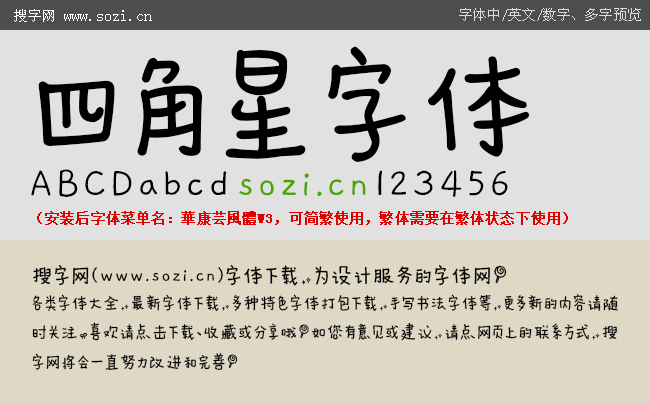
四角星字體
搜字網(wǎng)給大家提供一款卡通手寫風(fēng)格的手機(jī)中文字體下載。名字叫四角星字體,這款手機(jī)字體是以仿照兒童手寫風(fēng)格的卡通手寫字體華康蕓風(fēng)體為原形,標(biāo)點(diǎn)被換成了有趣的卡通圖案,特別適合喜歡手機(jī)字體個(gè)性一些的朋友在手機(jī)上安裝使用。